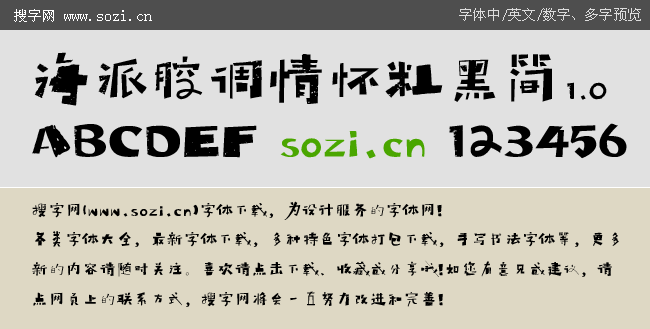
海派腔調(diào)情懷粗黑簡(jiǎn)1.0
搜字網(wǎng)提供一款海派腔調(diào)情懷粗黑簡(jiǎn)1.0中文字體下載,海派腔調(diào)情懷粗黑簡(jiǎn)字體是一款左粗右細(xì)、整體效果非常出眾的簡(jiǎn)體中文字體,適合應(yīng)用于廣告設(shè)計(jì)、名片設(shè)計(jì)、包裝印刷、產(chǎn)品設(shè)計(jì)等應(yīng)用。